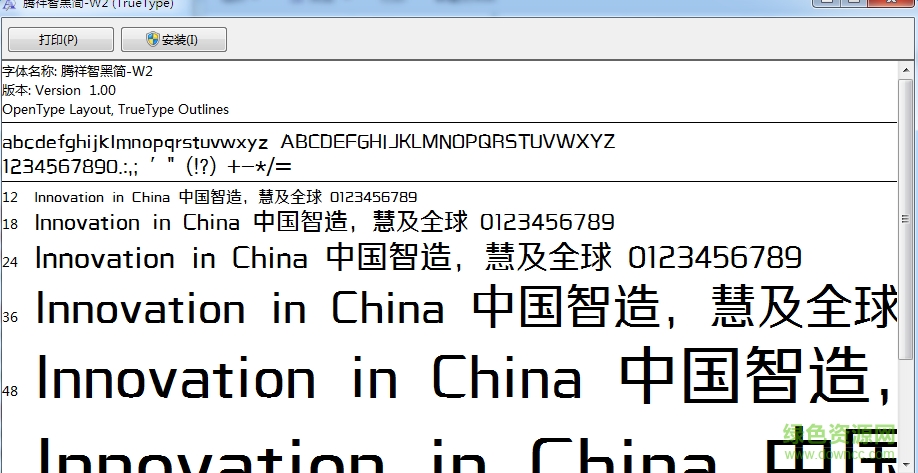
騰祥智黑w2字體是一款精心設(shè)計(jì)開(kāi)發(fā)的黑體字體,在保持傳統(tǒng)的黑體風(fēng)格與結(jié)構(gòu)方正的基礎(chǔ)上,修改了筆形,使其更加規(guī)范實(shí)用,需要用到不同字體的朋友可以來(lái)綠色資源網(wǎng)下載這款字體!
騰祥智黑-W2為細(xì)黑一款,整體筆畫(huà)看起來(lái)清晰,易于閱讀,筆畫(huà)纖細(xì)柔美適用于正文、屏顯、產(chǎn)品設(shè)計(jì)等。從設(shè)計(jì)到制作再到審稿及全部字形的校對(duì)每一個(gè)環(huán)節(jié)都精心完成,確保字庫(kù)質(zhì)量的精良!